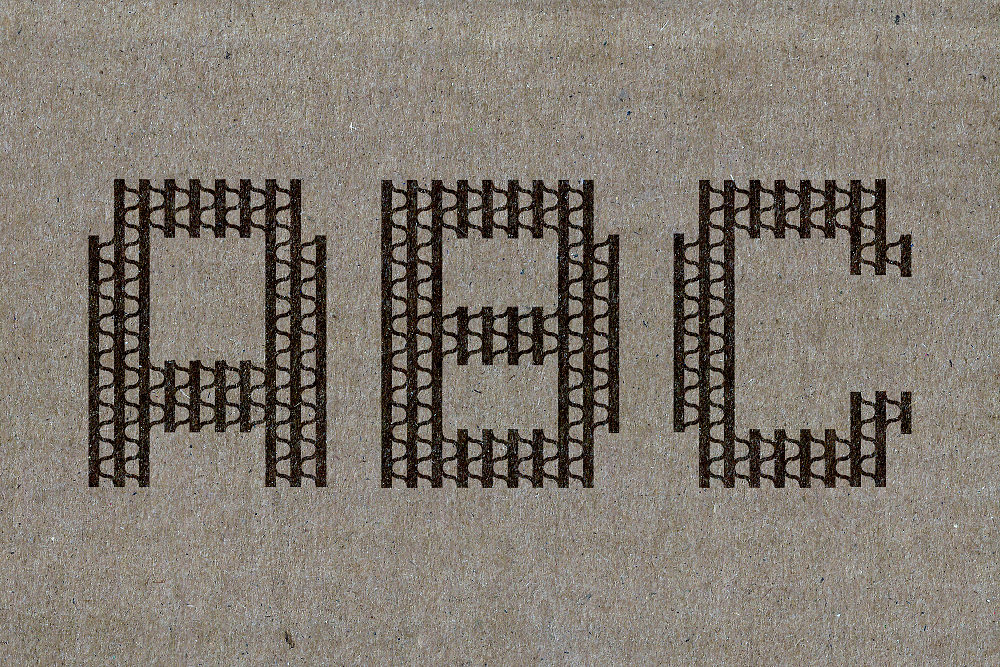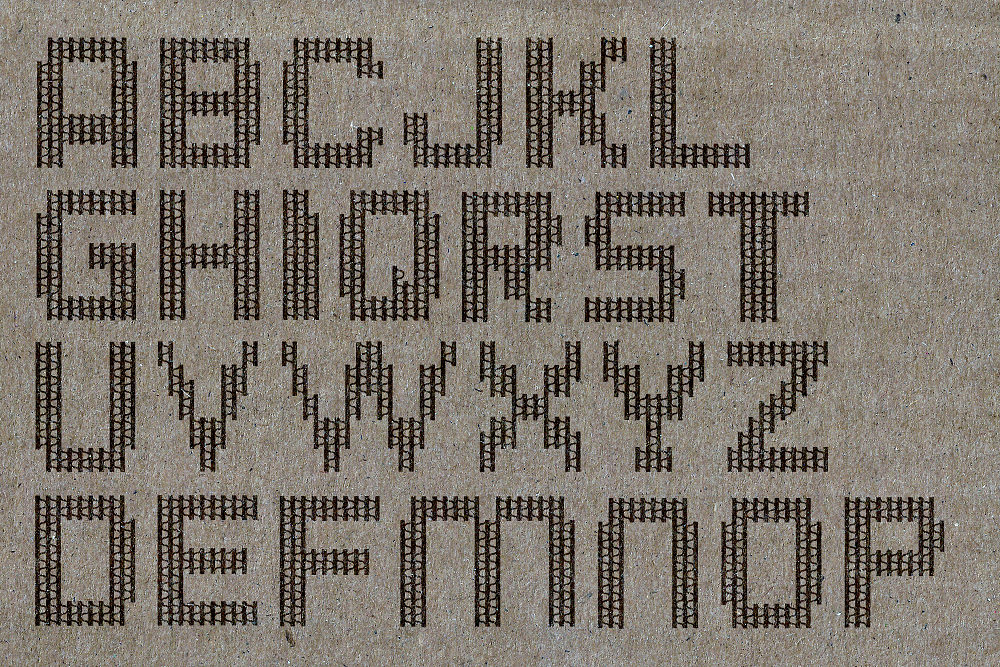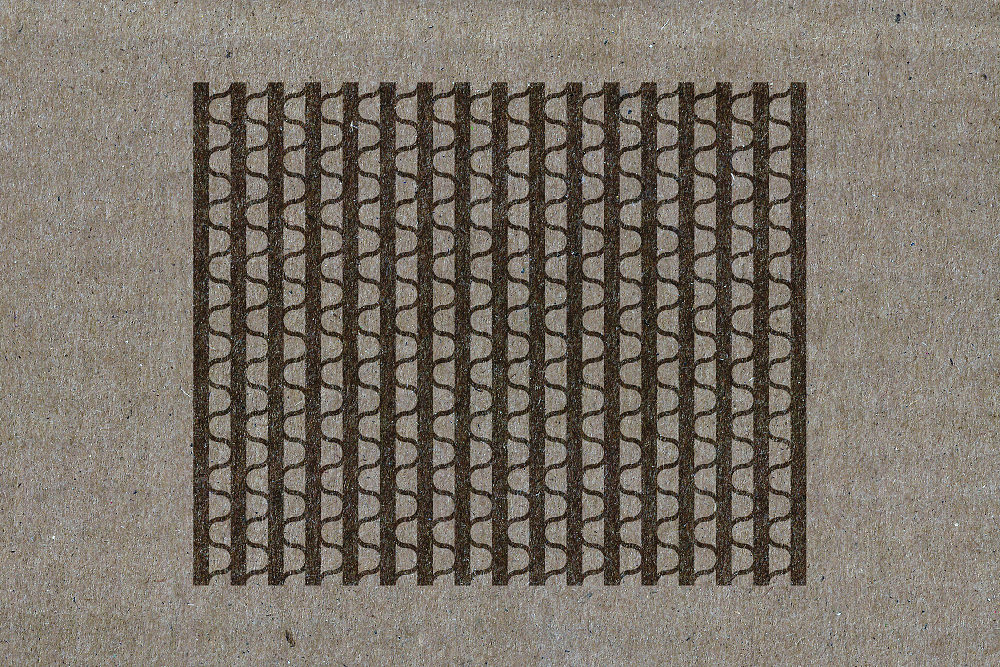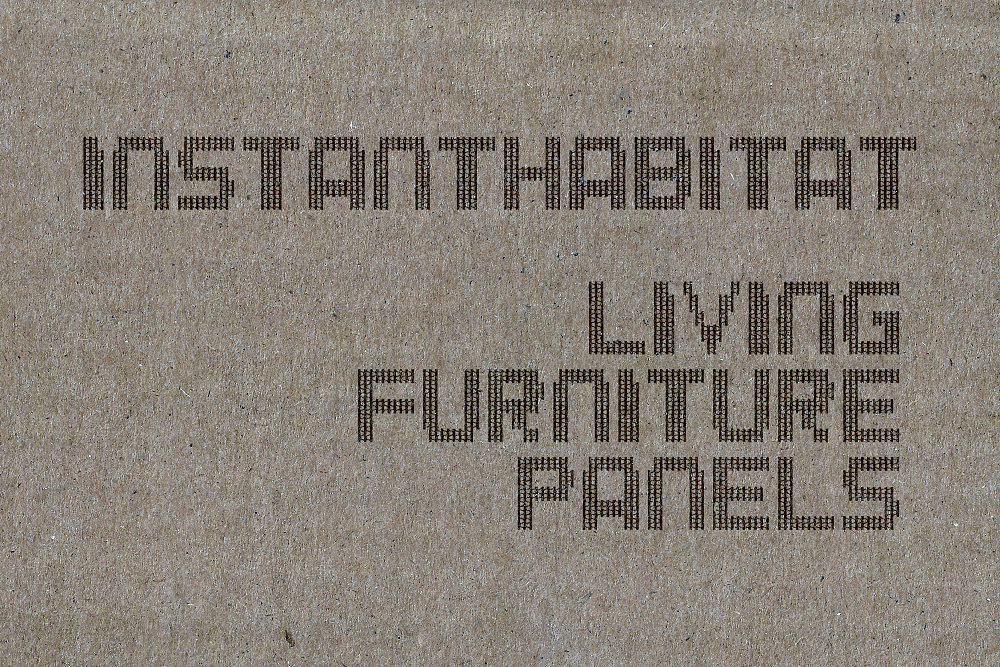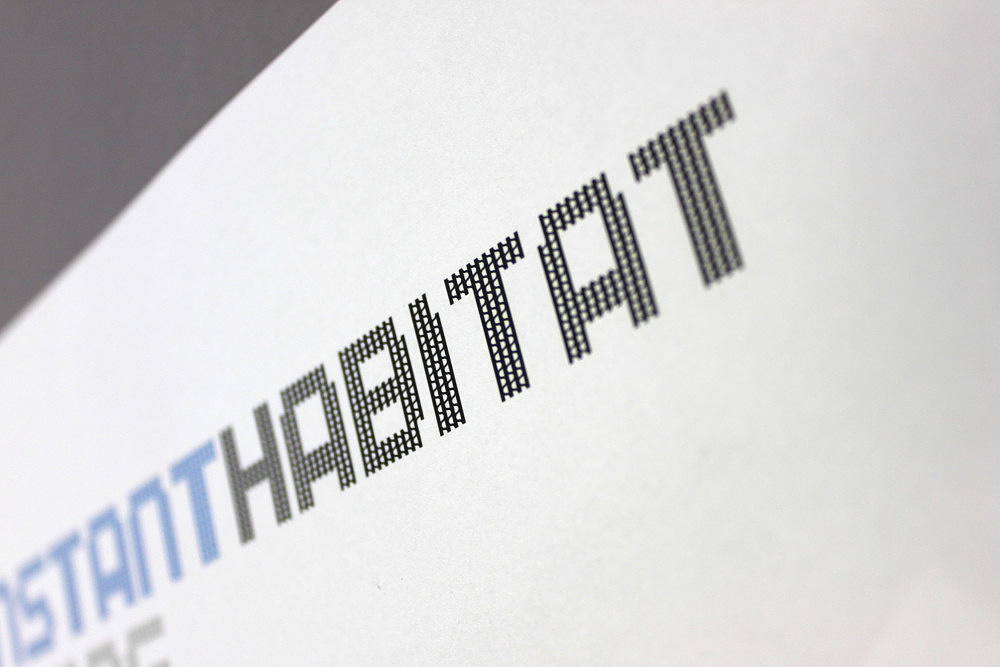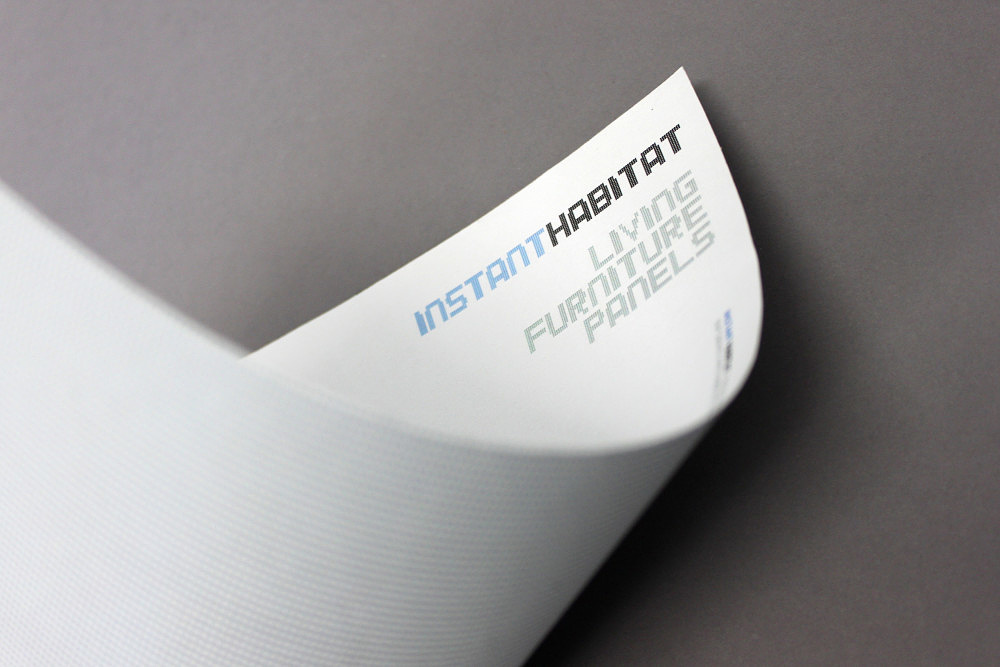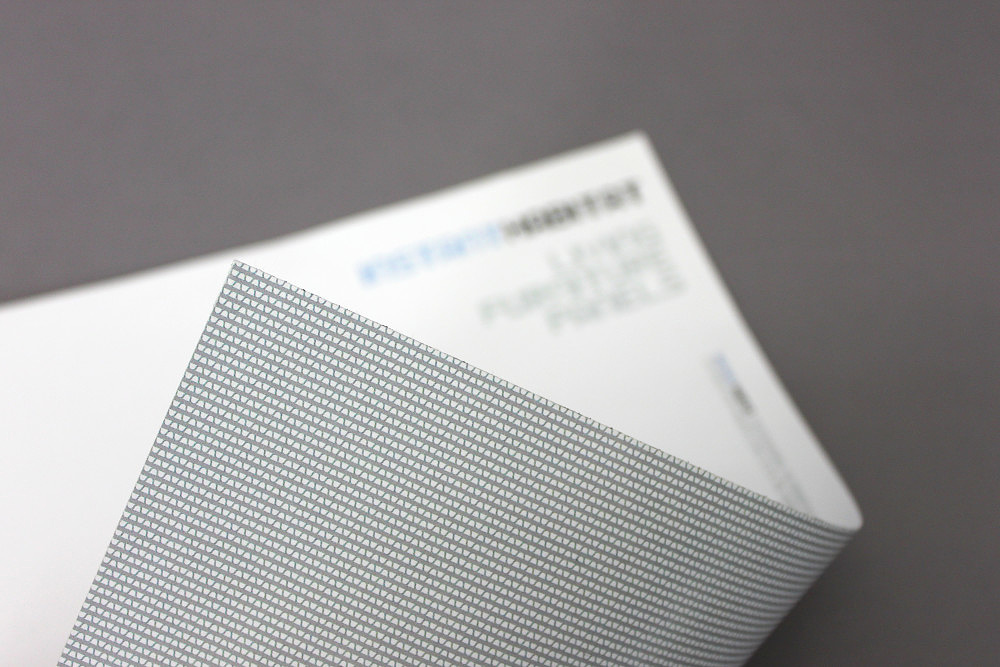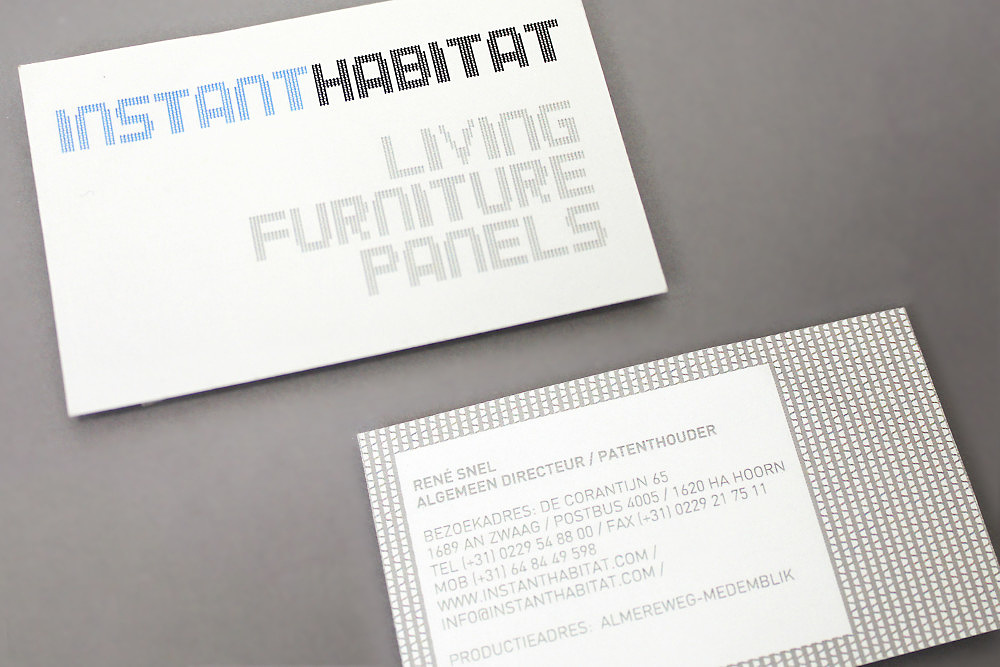
Introductie
Instant Habitat fabriceert constructie/bouw panelen gemaakt uit golfkarton (Correlite). Correlite maakt het mogelijk om in rampgebieden op locatie noodvoorzieningen te bouwen, bijvoorbeeld na een aardbeving.
Corrulite Font / Instant Habitat
Uitdaging
Ontwerp een nieuw merkconcept en –identiteit.
Resultaat
A nieuw letterype, merkconcept, identiteit en logo ontwerp gebaseerd op golfkarton.